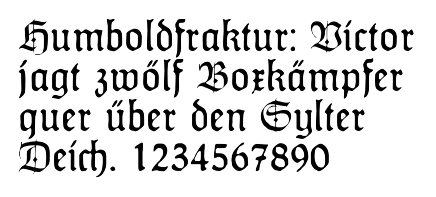
61 Schriftarten Für Tattoos
Die schrifarten für tattoo mit graffiti effekt sind eine besondere modernisierte variante der kaligraphie. 03 01 2021 erkunde marta jesmanowiczs pinnwand tattoo schriftarten auf pinterest.
Mit solchen schriftarten kann der tätowierer ein ganzes bild schaffen entweder bunt oder schwarz weiβ.
Schriftarten für tattoos. Die schriftarten für tattoos sind zahlreich und deshalb fällt die entscheidung für die passende schrift manchmal schwer. 01 07 2018 erkunde daniela ohmers pinnwand rosen tattoo umriss auf pinterest. Damit kann die aussage entweder gelungen in szene gesetzt oder völlig unlesbar werden.
Lettering styles include tribal traditional sailor blackletter fancy cursive script etc. Weitere ideen zu tattoo schriftarten klebetattoos temporäre tattoos. Bereit zum individualisieren und teilen auf facebook und twitter.
Schriftarten für tattoo mit graffiti effekt. Reine text tattoos liegen heute immer mehr im trend und immer mehr menschen wählen worte namen kurze zitate oder bedeutsame redewendungen um sich durch ihre tattoos auszudrücken. Tattoo schriftarten können verwendet werden um sich eine vorschau für textbasierte tätowierungen zu erstellen und so einfacher über diese zu entscheiden.
21 03 2020 erkunde anna kellers pinnwand tattoo schriftarten auf pinterest. Weitere ideen zu tattoo schriftarten tätowierungen tattoo ideen. Egal ob sie sich einen namen ein lebensmotto oder inspirierendes zitat stechen lassen ist die schriftart von zentraler bedeutung.